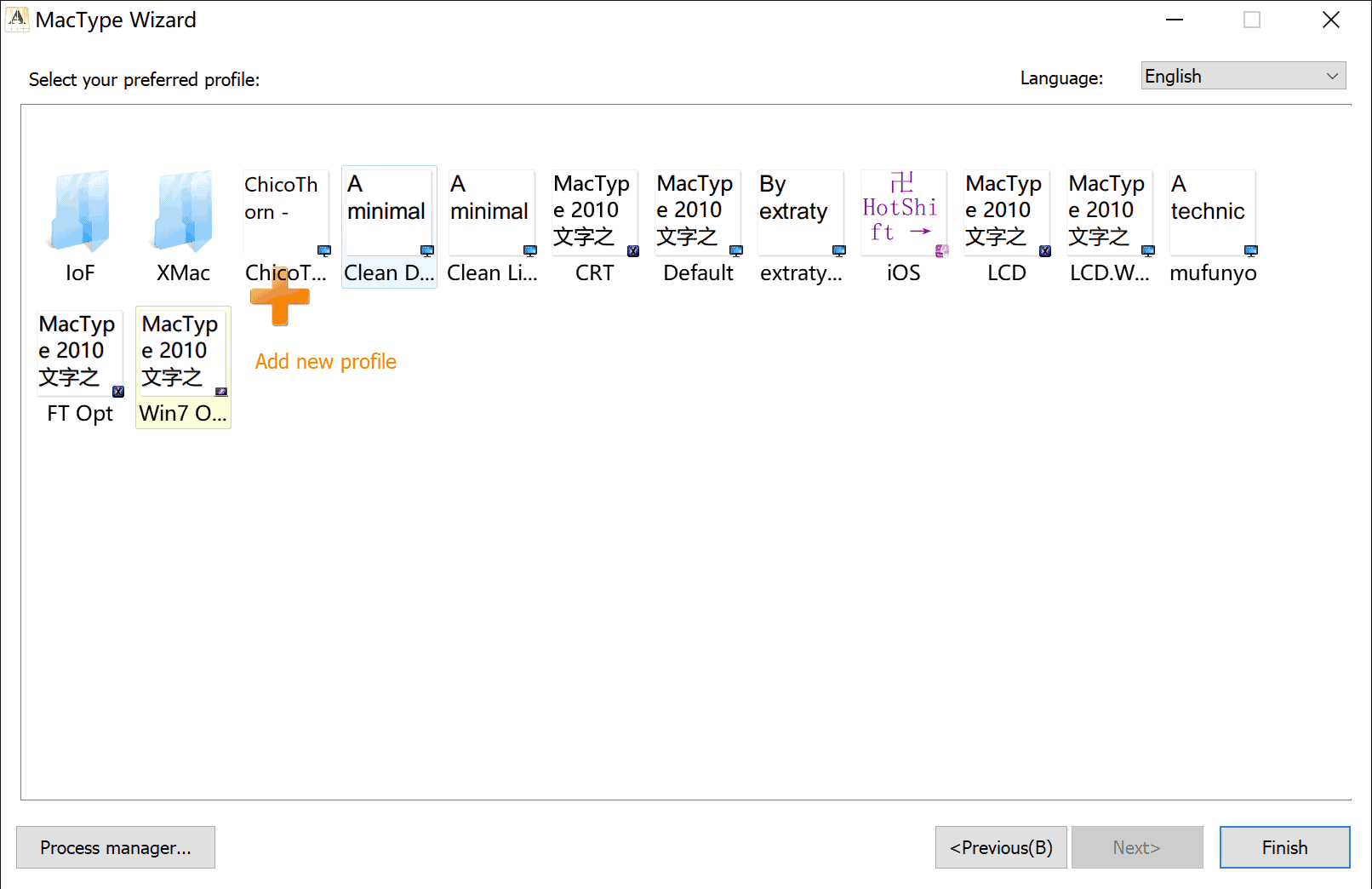
MacType 配置指南:优化 Windows 系统字体渲染效果
软件说明
MacType 是非常著名的系统字体美化软件,MacType 原名(GDI++),它的字体渲染引擎能使文字显示得更清晰、更有立体感。MacType 是一个字体渲染引擎,通过接管 Windows 系统的 GDI 字体渲染,使文字显示得更清晰、更有立体感,实现比 Mac 系统更华丽的字体渲染效果。支持 WinXP、Vista、Win7、Win8、Win10、Win11 操作系统。MacType 内置多种字体渲染配置方案为您带来更方便、更美的视觉体验,XMAC 系列方案需要配合 XHEI 字体使用。
大概的效果是这样的,可以看图中的字体